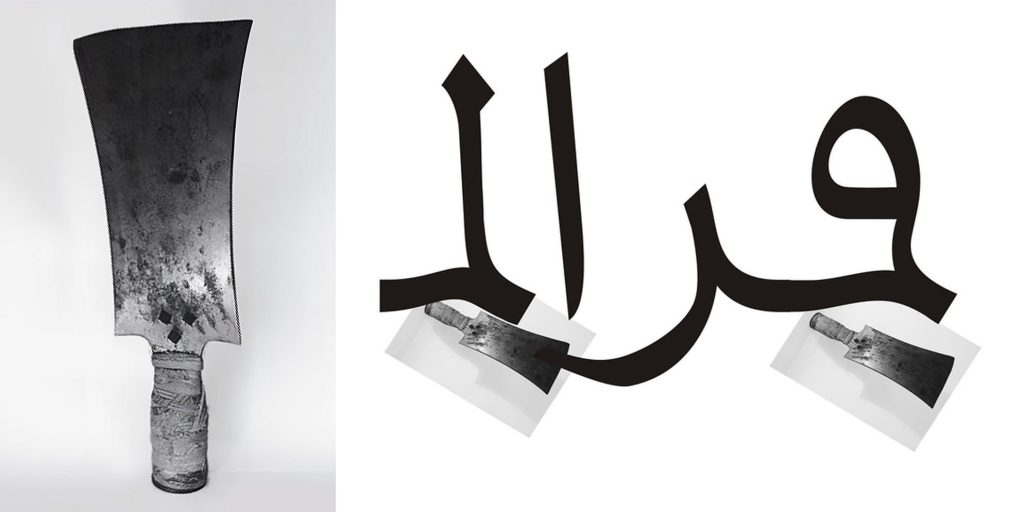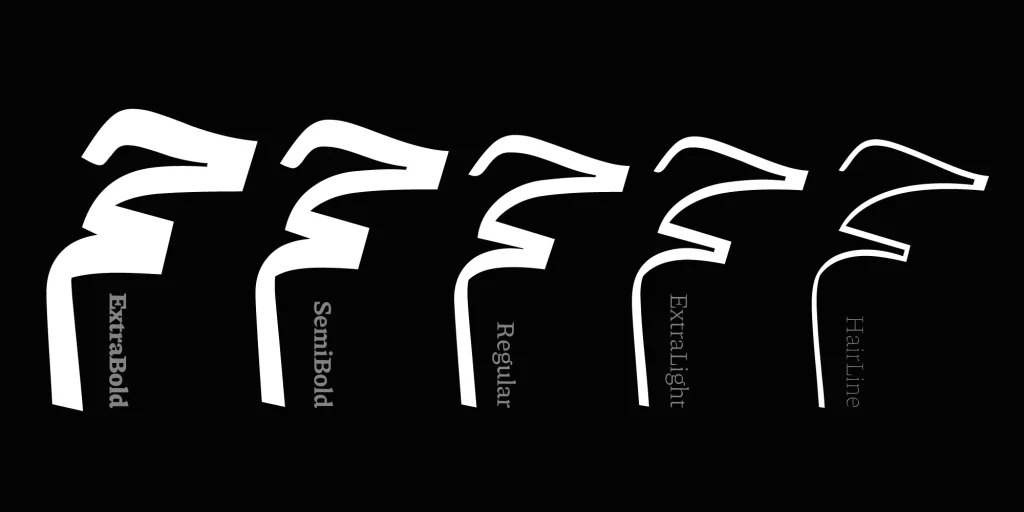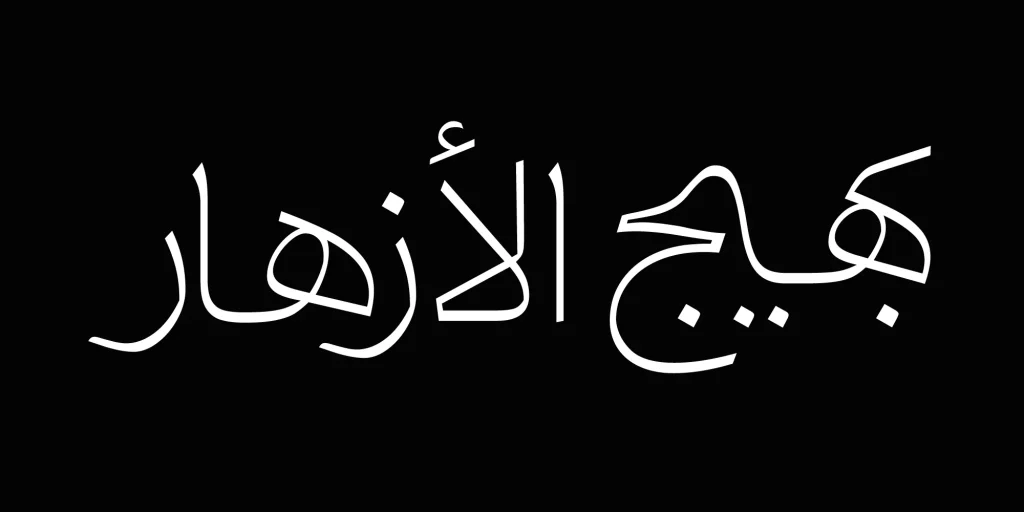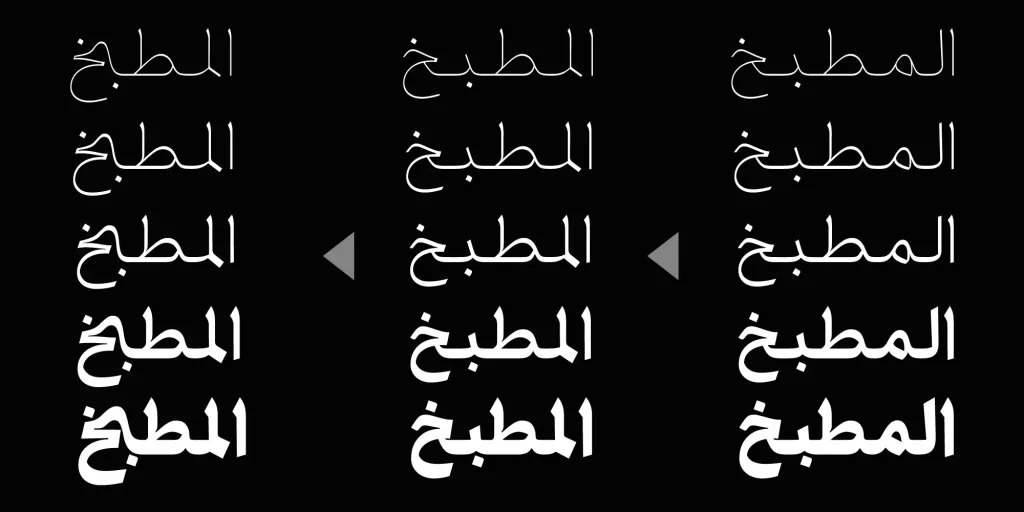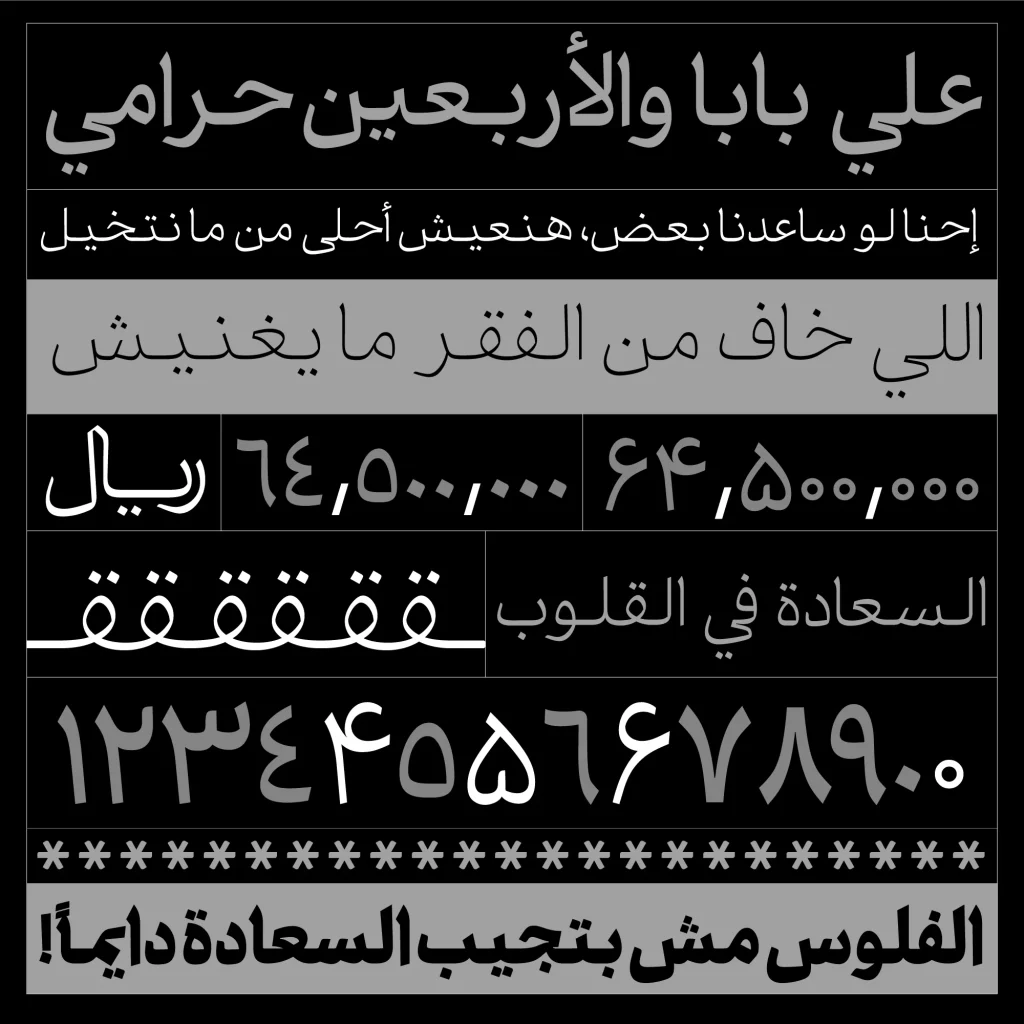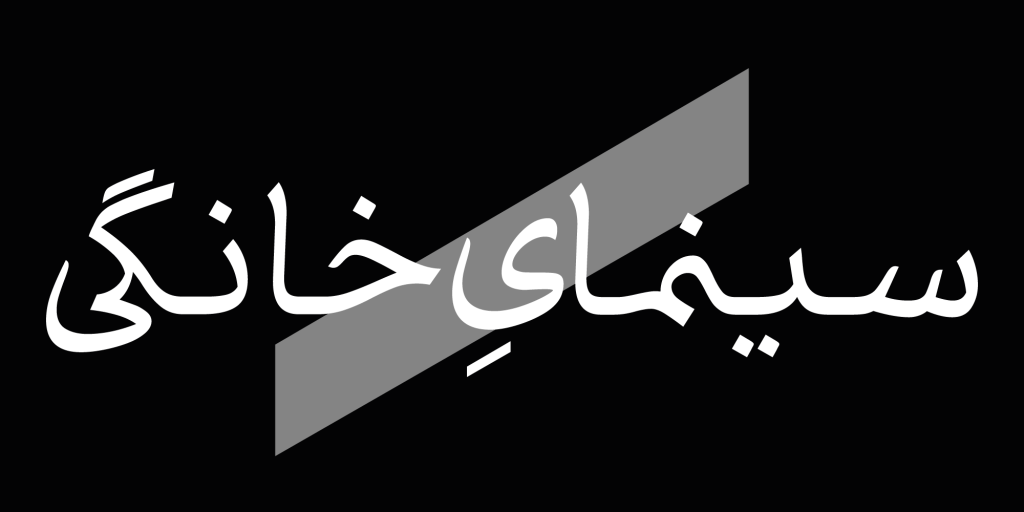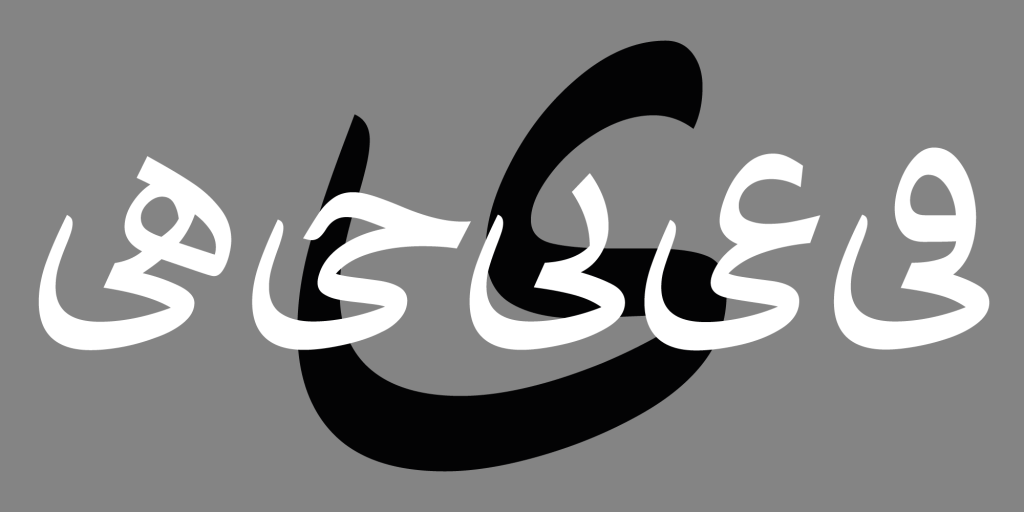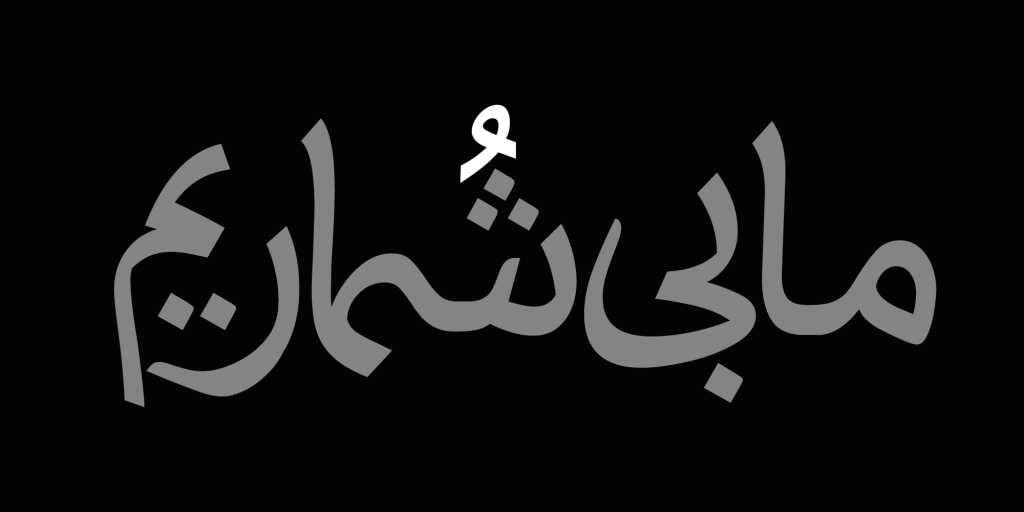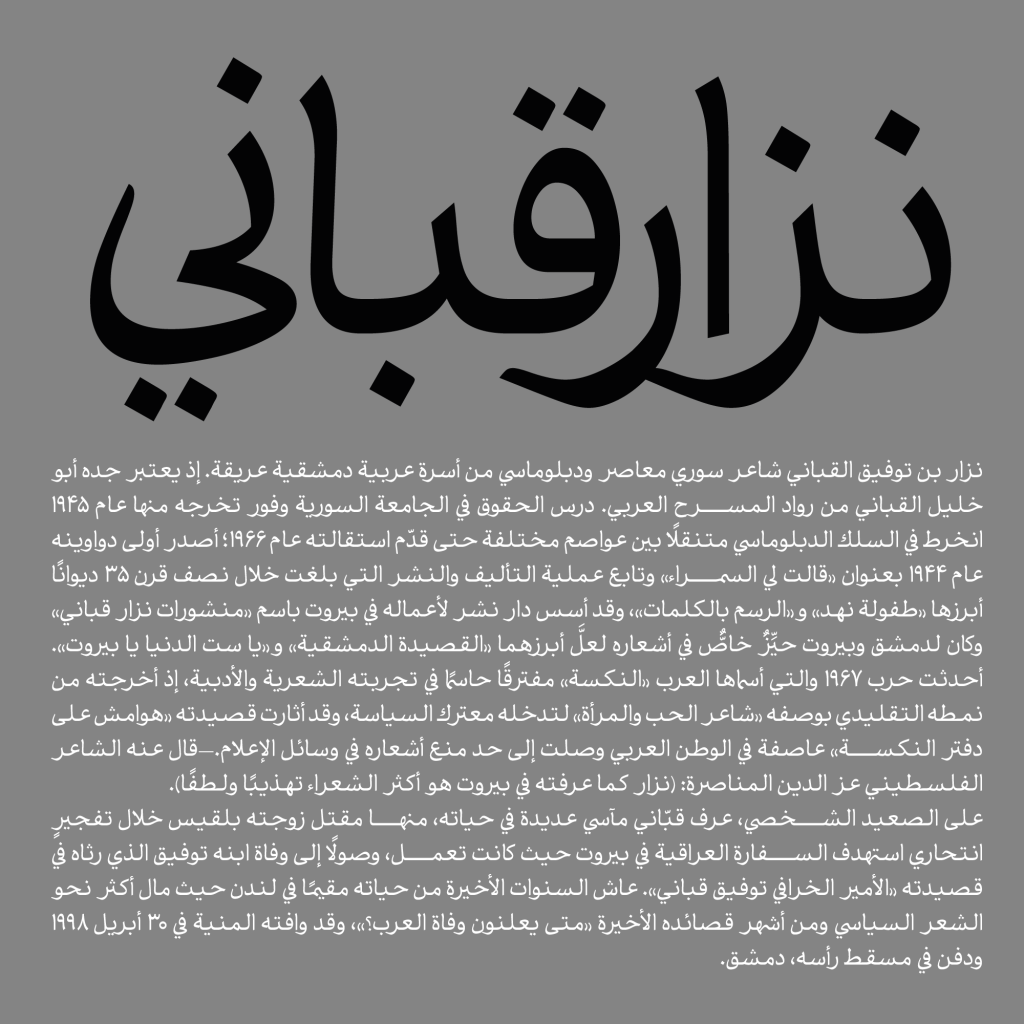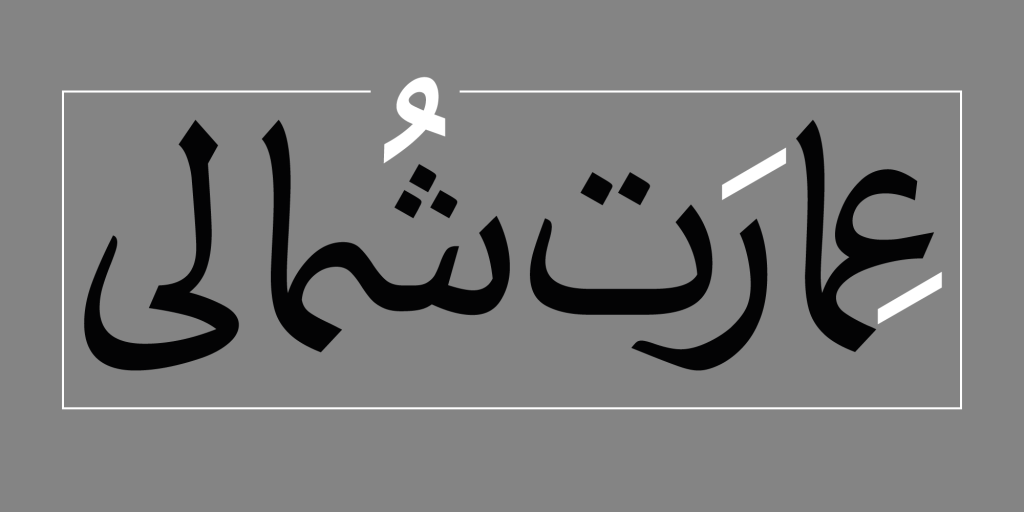
تایپ فیس دامون قلمی با بیش از 16 سال همت و زحمات جناب آقای دامون خانجان زاده دارای امکانات و قابلیت های فراوانی برای علاقه مندان به صنعت تایپوگرافی است . با ما همراه باشید.
فونت دامون
فونت دامون از سال 1387  متولد و نخستین نسخه خود را تجربه نمود. این قلم که از خانواده خط خوشنویسی نسخ است با دارا بودن تنوع وزنی بسیار گسترده تمامی نیازهای طراحان را مرتفع می نماید . دامون با داشتن بیش از 20 وزن مختلف از نازکی تار مو HairLine تا بسیار سنگینِ Heavy هر آنچه برای تنوع وزن در سلسله مراتب تایپوگرافی نیاز دارید در دل خود جای داده است.
در سال 1402 با حمایت گروه دانش بنیان فونت ایران این میراث گرانقدر و زیبا باز طراحی گردید تا در اختیار شما عزیزان قرار گیرد.  لازم به توضیح است که دامون خانجانزاده، طراحی با سابقه و صاحب سبک است که شهرت جهانی دارد. این قلم  تازه‌ ترین اثر او و حاصل سال‌ها تجربه است.
امکانات فراوان و پشتیبانی از زبان های مختلف
وجود ترکیبات فراوان که تعداد آن به بیش از 1000 ترکیب دو و سه حرفی است . پویایی و تنوع بی نظیری را به این تایپ فیس می دهد. همانطور که در ابتدای این مطلب گفته شد قلم دامون دارای امکانات و قابلیت های حرفه ای بی شماری نیز است. از جمله این امکانات می توان به فارسی کردن اعداد در بخش دلخواه/ هم عرض کردن اعداد/ تراز عمودی اعداد/ استفاده از ترکیبات در موبایل/ ریال و تومان فشرده/ حروف کشیده/ و هر آنچه یک فونت متن و …. اشاره نمود.
دامون با پشتیبانی از زبان های مختلف از جمله کوردی، انگلیسی، اردو ، عربی  و …دارای ویژگی چند زبانی هم می باشد. در تصاویر زیر می توانید نمونه هایی زیبا از فونت دامون را که برای شما عزیزان مهیا نموده ایم استفاده کنید.